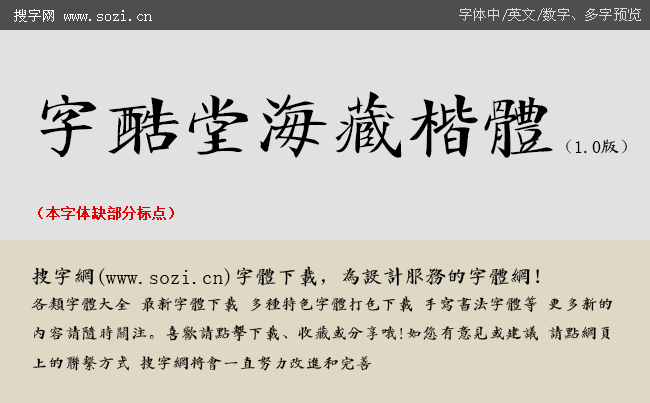
字酷堂海藏楷體
搜字網(wǎng)給大家提供一款字酷堂海藏楷體中文書(shū)法字體下載。該字體筆鋒犀利,線(xiàn)條張揚(yáng),字形藝術(shù)風(fēng)格十足,適合包裝設(shè)計(jì)、海報(bào)設(shè)計(jì)、畫(huà)冊(cè)設(shè)計(jì)等廣告設(shè)計(jì)場(chǎng)合使用。
- 風(fēng)格類(lèi)別: 手寫(xiě)書(shū)法體